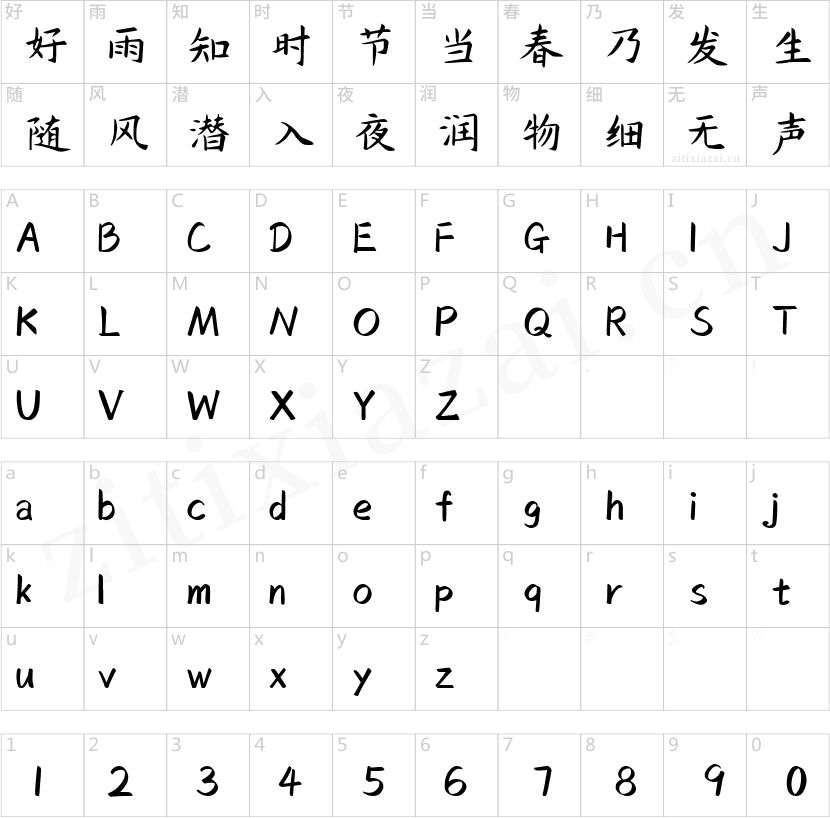
字魂1001号-丹青行书
字魂字体字小魂丹青行书字体是由字魂创意字库设计并生产的一款可商用的字体,被收录于字小魂系列。该字体支持GB-2312标准以及最新的字魂ZH7144标准,包含9403个中文、字母、符号和数字,字体类型偏向毛笔书法,具有简约、时尚的风格,在市面上广泛用于社交、运动户外、包装印刷等场景。